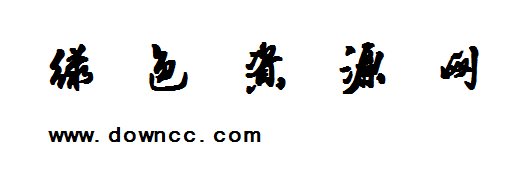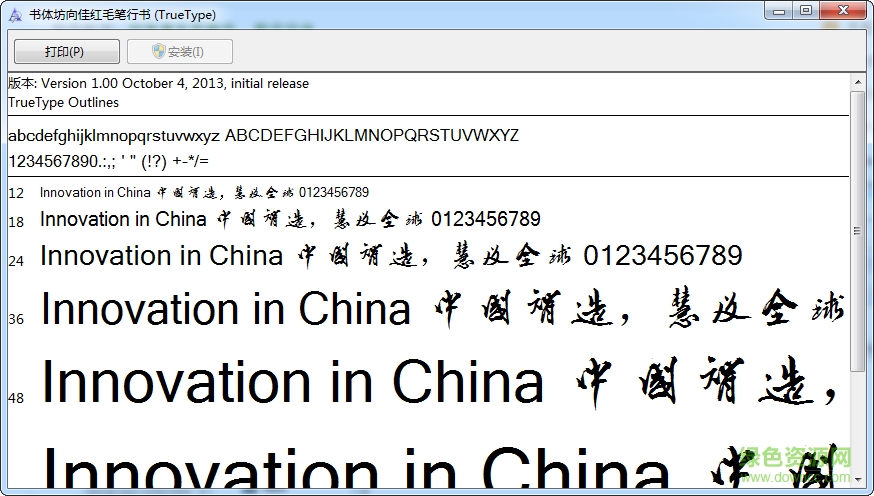
書體坊向佳紅毛筆行書字體是一款常規(guī)毛筆字體,該字體構(gòu)造端正,筆畫飛揚(yáng),充滿韻味,可應(yīng)用于各個(gè)方面,有需要者歡迎在綠色資源網(wǎng)下載!
向佳紅毛筆行書字體由書體坊基于向佳紅先生親自書寫的書法作品開發(fā)而成,版權(quán)歸向佳紅所有。
向佳紅毛筆行書是一款非常漂亮的中文書法字體,字形飄逸大方,適用于廣告設(shè)計(jì)、印刷、企業(yè)LOGO設(shè)計(jì)、商標(biāo)注冊、店招、名稱、包裝設(shè)計(jì)等應(yīng)用字體。